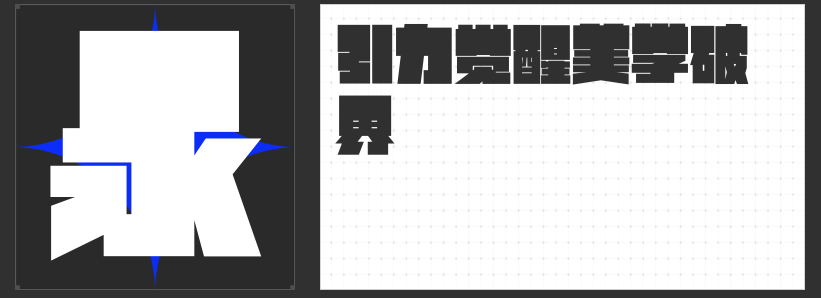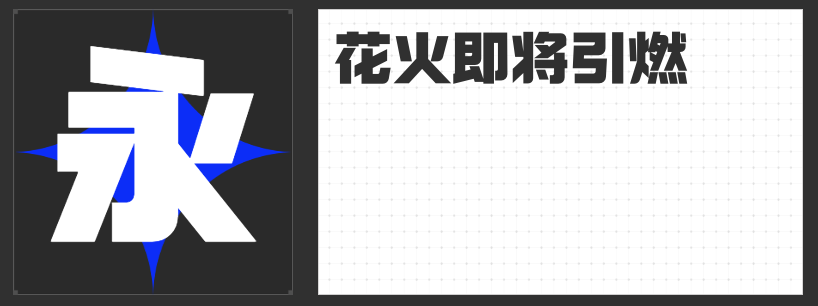
力量美学新标杆:四款极具视觉张力的设计字体推荐
在当代视觉设计中,力量感不仅是视觉冲击的呈现,更是品牌精神与情感张力的具象化表达。本文精选四款突破传统框架的创意字体,从结构美学到视觉语言,深度解析其如何通过字形设计传递强劲的视觉能量。
一、励字开拓者简 超黑
这款字体以建筑美学为灵感,通过绝对对称的几何结构构建视觉秩序。其方正字型与扩大中宫形成稳定框架,横竖笔画以直角切割收尾,消除所有曲线元素,形成如金属构件般的冷峻质感。内部空间的均匀分布强化了字体的整体性,而去钩化处理与竖向撇捺设计则创造了独特的镜像视觉效果。这种将理性思维注入字形的创新,使其成为科技、工业领域设计的理想选择。
二、励字勇敢黑简 超黑
作为无衬线字体的极致演绎,勇敢黑通过极粗笔画的视觉压迫感传递直击人心的力量。设计师刻意弱化撇捺的尖锐特征,采用平直均匀的横竖结构,确保远距离识别的清晰度。这种去装饰化的设计语言,使字体在标题、标志等场景中形成强烈的视觉焦点,其醒目程度甚至超越传统粗黑体,成为需要瞬间抓住注意力的设计场景首选。
三、励字铁拳简 超级黑
突破传统黑体的机械感,铁拳简通过饱满的块面结构与圆角折笔的矛盾组合,创造出刚柔并济的视觉张力。超级粗的笔画赋予字体如金属锻造般的厚重感,而折角处的圆润处理则巧妙中和了生硬感,形成"铁拳出击"的动态意象。这种将力量与温度融合的设计哲学,使其在运动品牌、军事主题等需要展现强韧气质的领域表现卓越。
四、励字造大头黑 超级粗
作为逆反差字体的创新典范,造大头黑通过"上重下轻"的非常规结构打破视觉平衡,顶部夸张的笔画粗度与底部纤细线条形成戏剧性对比。这种颠覆传统的设计语言,在保证识别性的前提下,创造出如浮雕般的立体层次感。其棱角分明的几何轮廓与平稳重心,使字体在保持厚重感的同时,蕴含着随时爆发的动态势能。
这四款字体通过结构创新与视觉语言重构,重新定义了力量感在字体设计中的表达维度。无论是追求理性秩序的科技品牌,还是需要传递强韧气质的运动领域,这些突破传统框架的创意字体,都能为设计注入令人过目难忘的视觉能量。